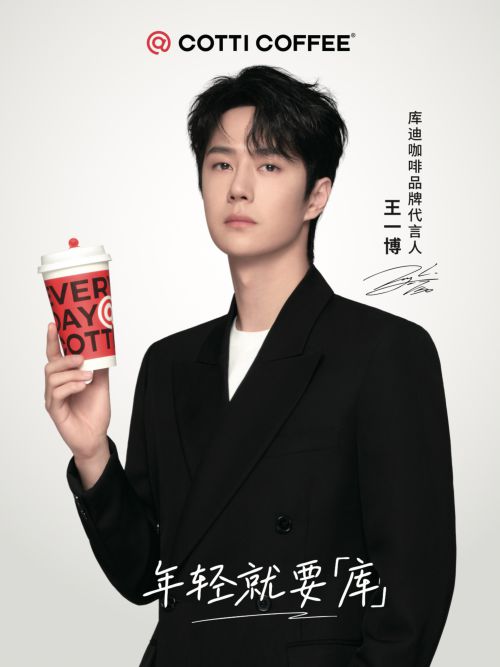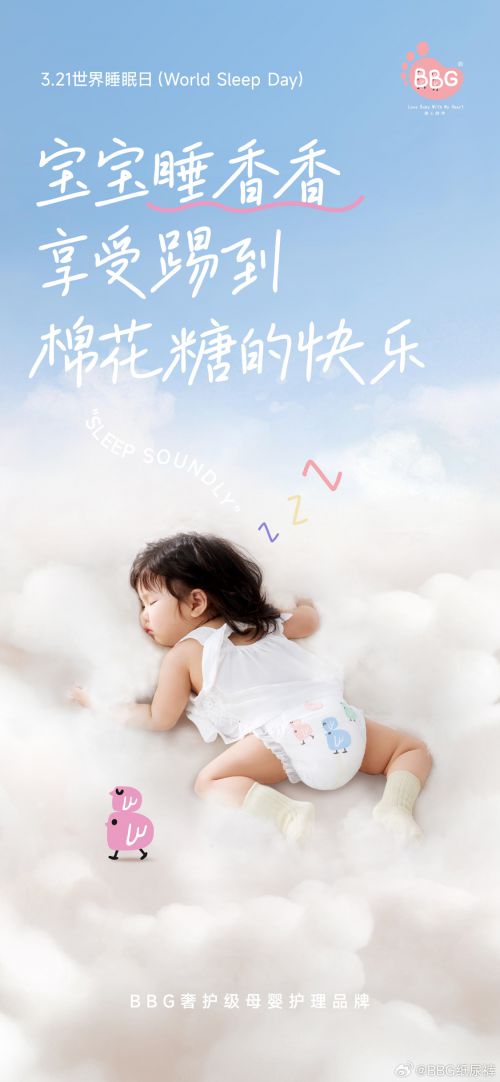
上首追光手写体
字库品牌: 上首造字 >
本套字对字体的笔画加以夸张处理,主要用相对笔直的线条来书写,拉长了撇、捺、点等笔画,简化了勾这个笔画,并且有独特的断笔、连笔处理。看起来就像几束“光”穿梭交错,有“光”的迅捷、直挺之感。整体文字显得简约、潇洒、奔放,张扬却有序,富有个性,传达一种积极向上的态度,给人留下深刻鲜明的印象。适用于搭配海报、专辑、书信、商业广告等大众属性。